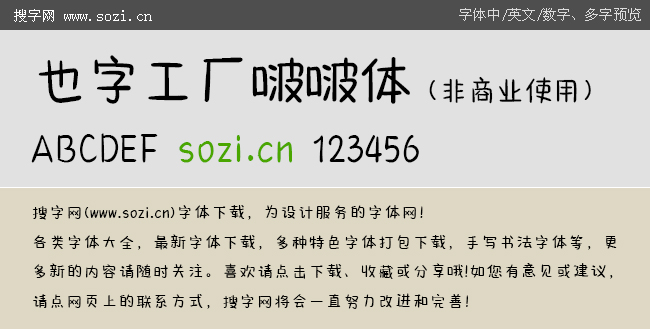
也字工廠啵啵體
搜字網(wǎng)給大家提供一款也字工廠啵啵體(非商業(yè)使用)中文字體下載,也字工廠啵啵體是一款卡通風(fēng)格字體,字體富有變化,充滿童真,趣味性十足。具有很好的視覺效果。適合應(yīng)用于藝術(shù)設(shè)計、平面宣傳設(shè)計、網(wǎng)頁設(shè)計、海報設(shè)計等應(yīng)用(此字體為個人非商用版,商用可以聯(lián)系:官方網(wǎng)址:https://yefont.com/home,聯(lián)系方式:13798980448)。